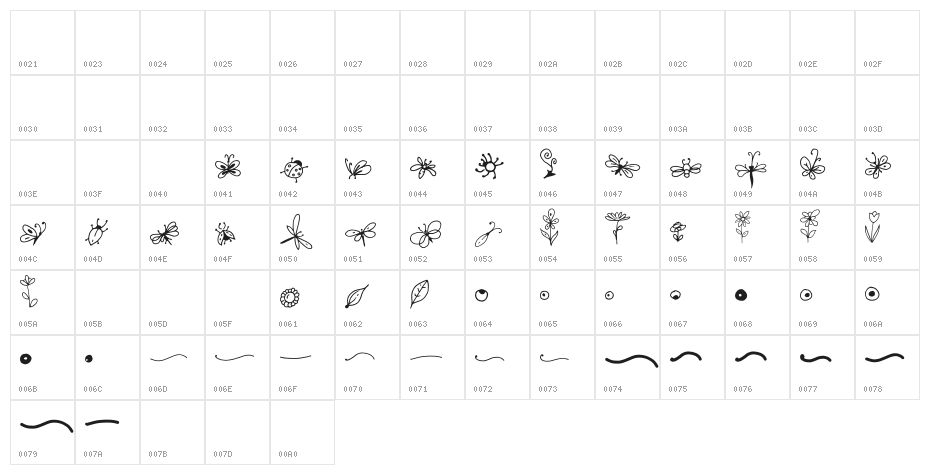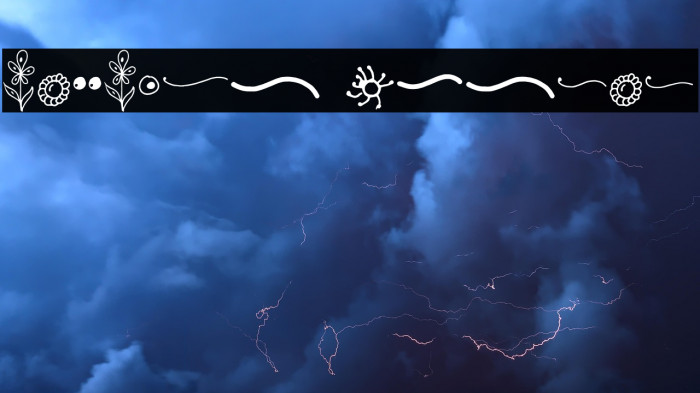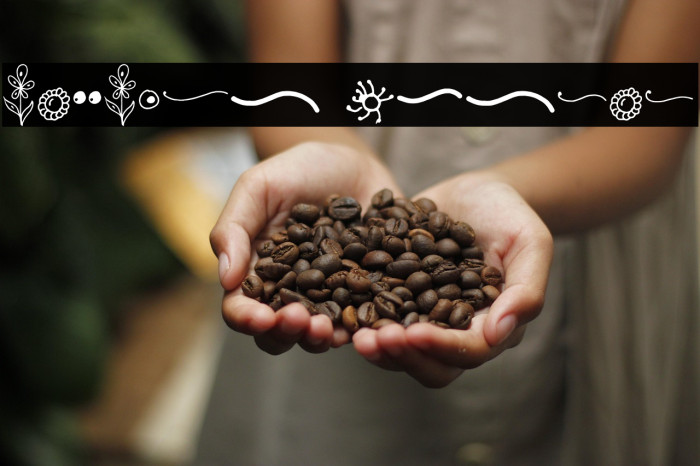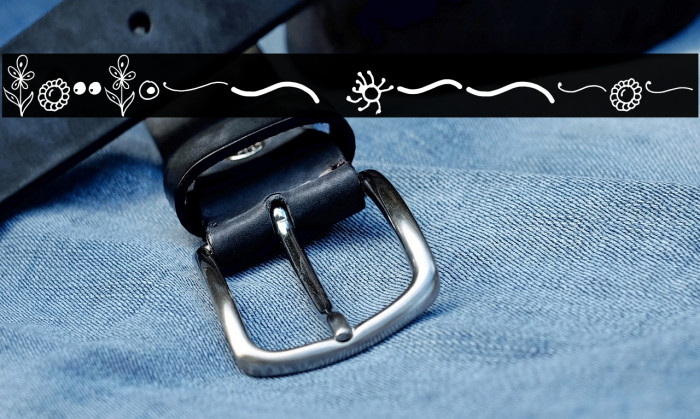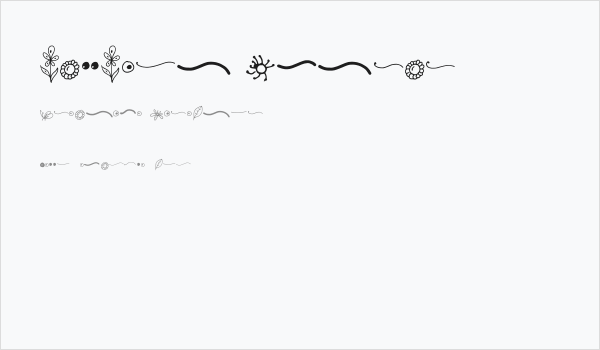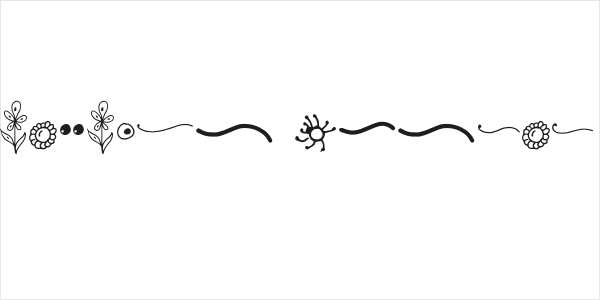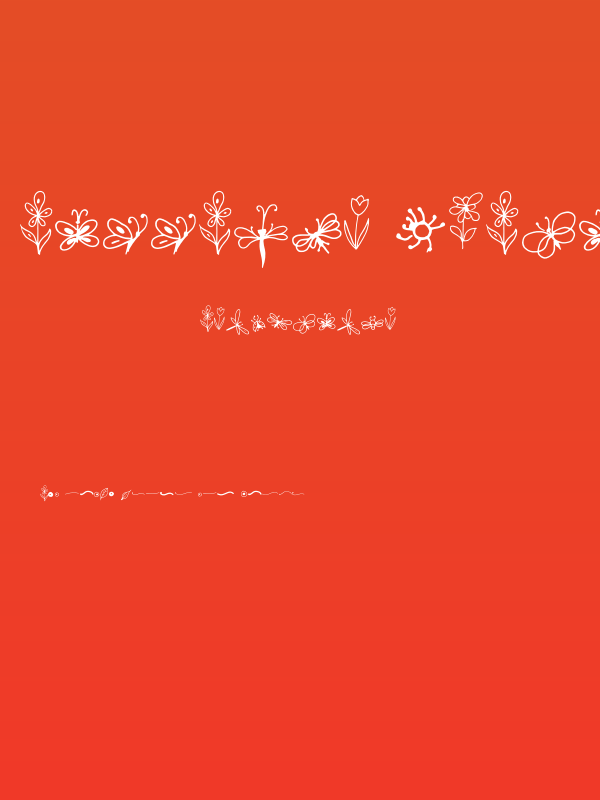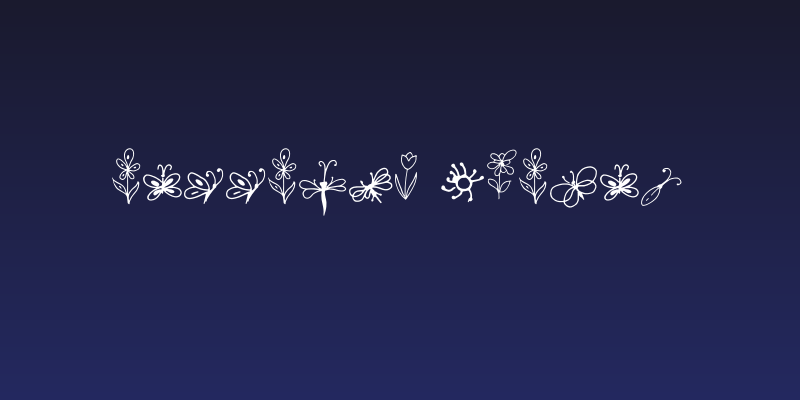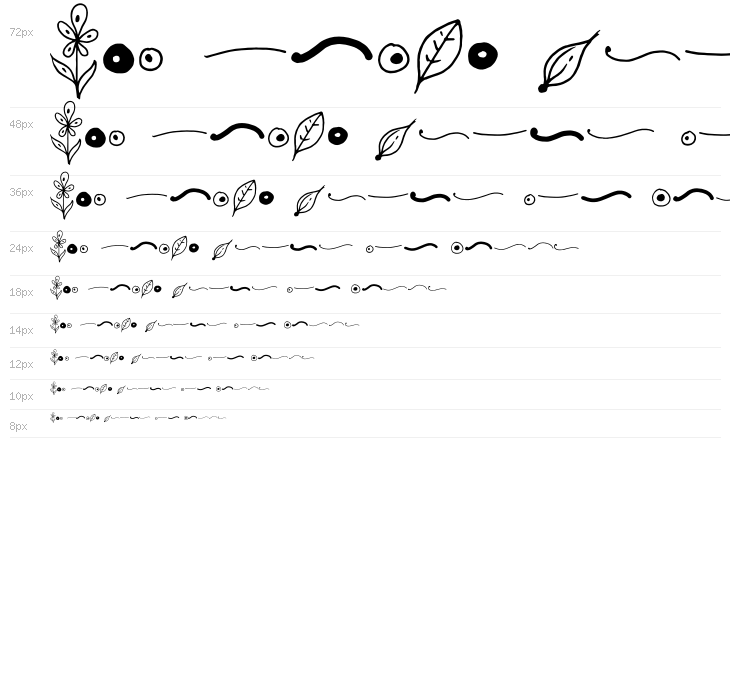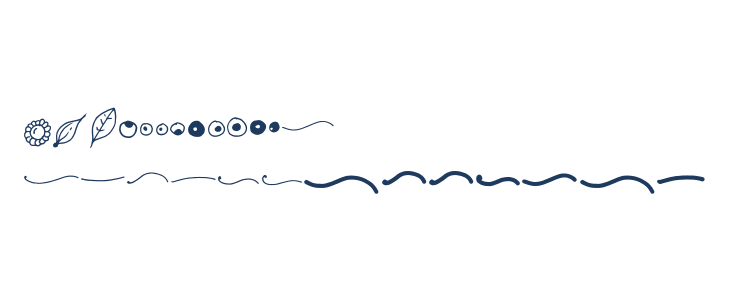
TallTiny Extras Font
| Gesamtstil | Decorative, Whimsical, Hand-drawn |
| Anwendungsfall | Decorative elements, embellishments, borders, accents. |
| Vorgeschlagene Projekte | Scrapbooking, children's books, greeting cards, invitations, decorative borders, bullet journals, craft projects. |